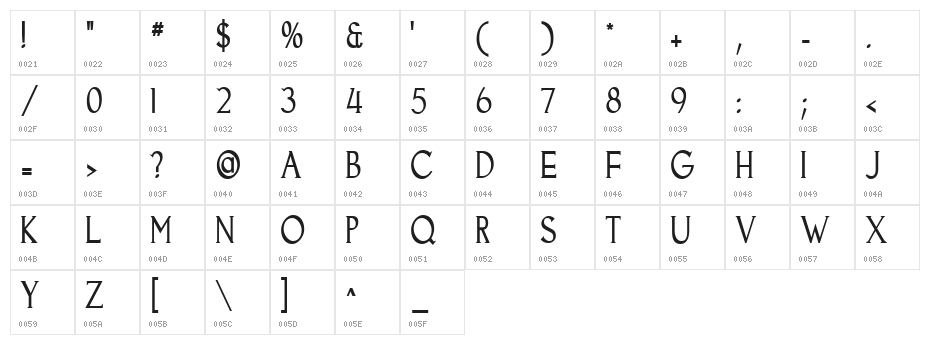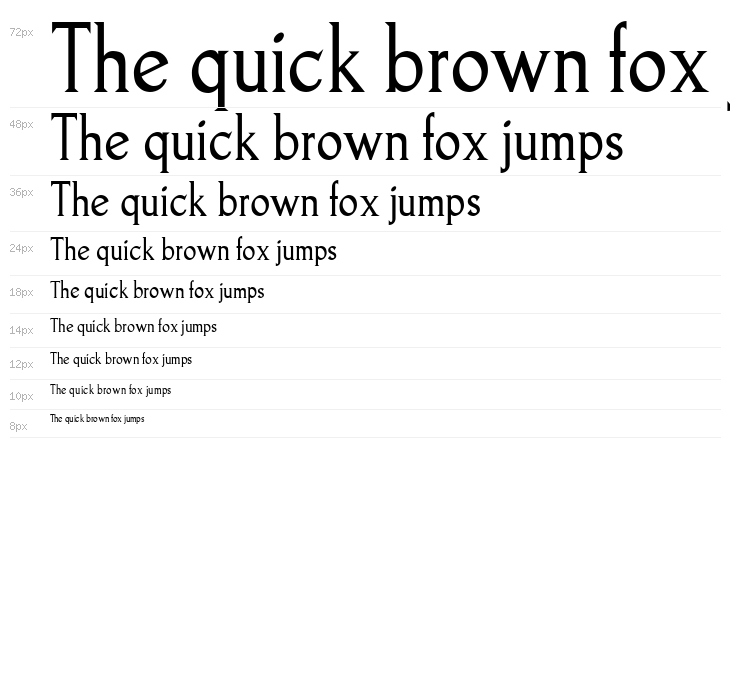
Goodfish Font
| श्रेणियाँ | Serif |
| समग्र शैली | Classic |
| उपयोग का मामला | Headlines, Body text, Logos |
| सुझाए गए प्रोजेक्ट | Ideal for editorial design, book covers, formal invitations, and branding projects that require a touch of sophistication. |